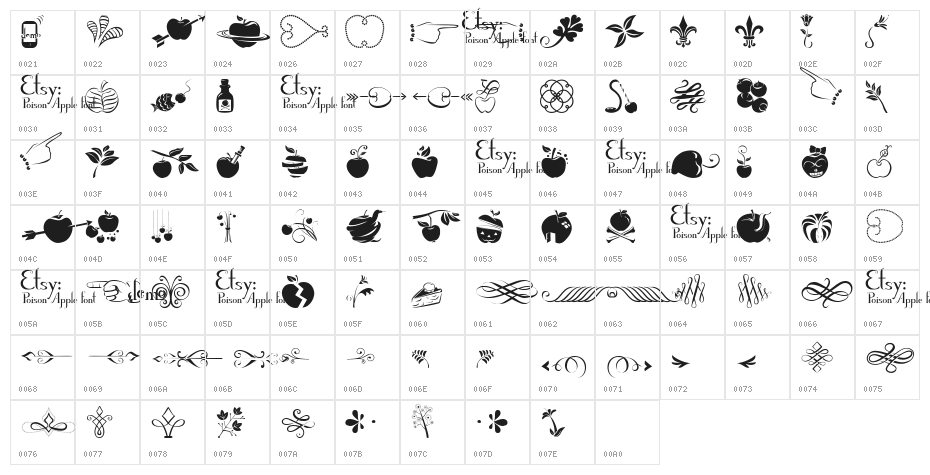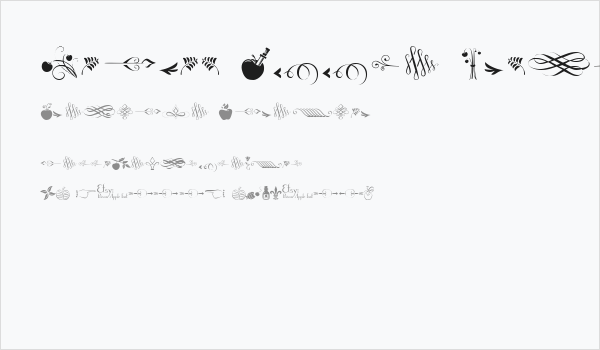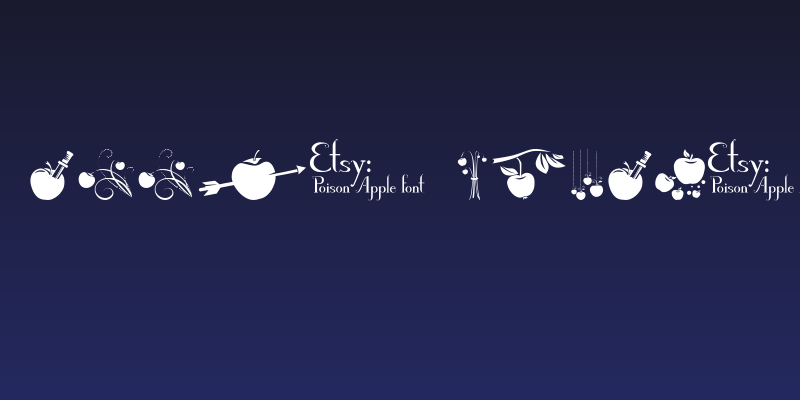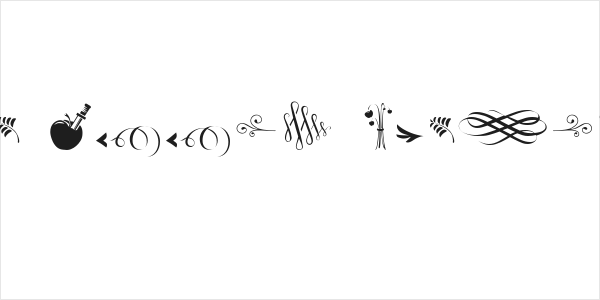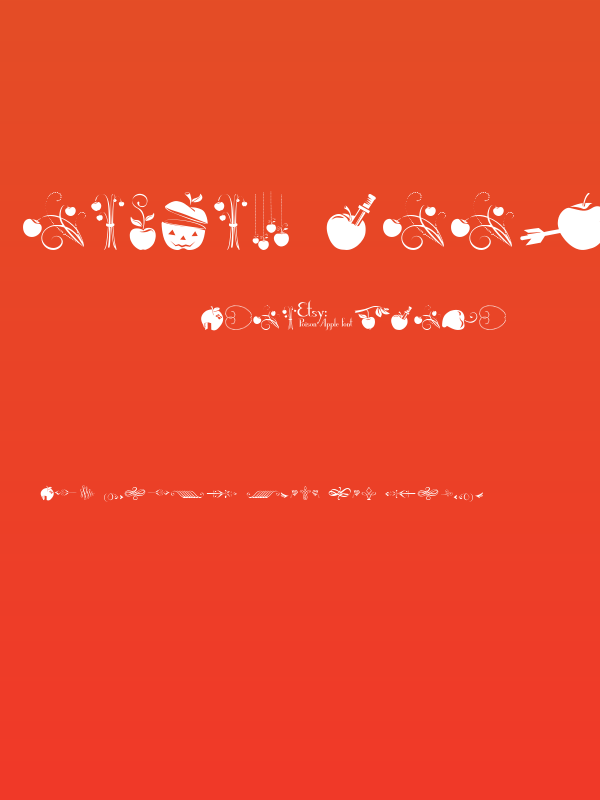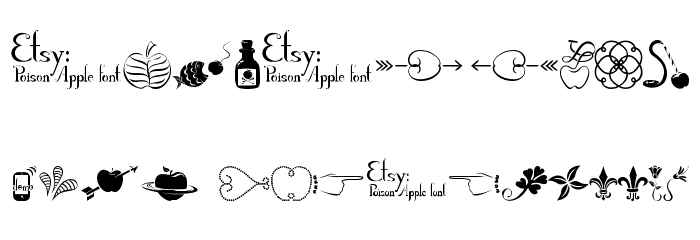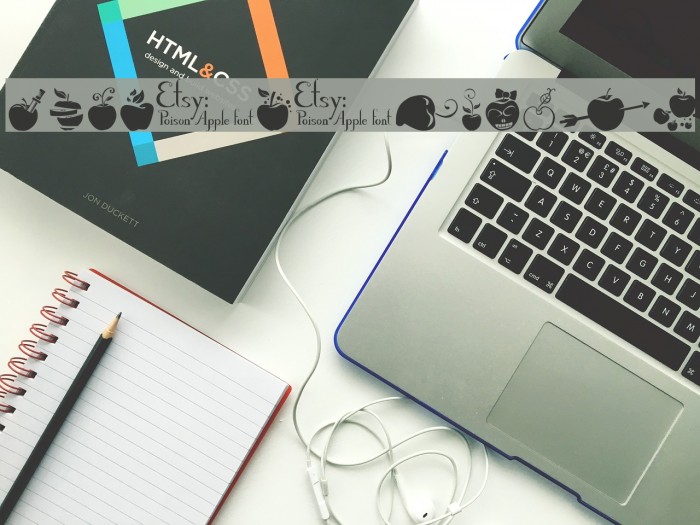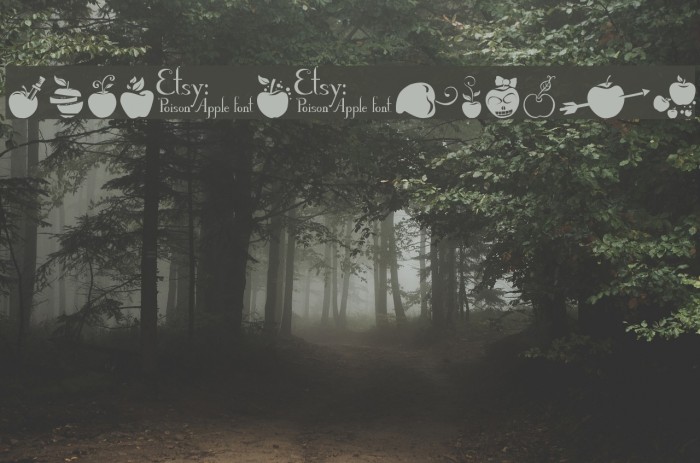
Poison Apple Ornaments 1 Font
| Caso de uso | Logos, Headlines, Decorative elements |
| Proyectos propuestos | Ideal for invitations, fantasy-themed graphics, children's book illustrations, and decorative posters. |